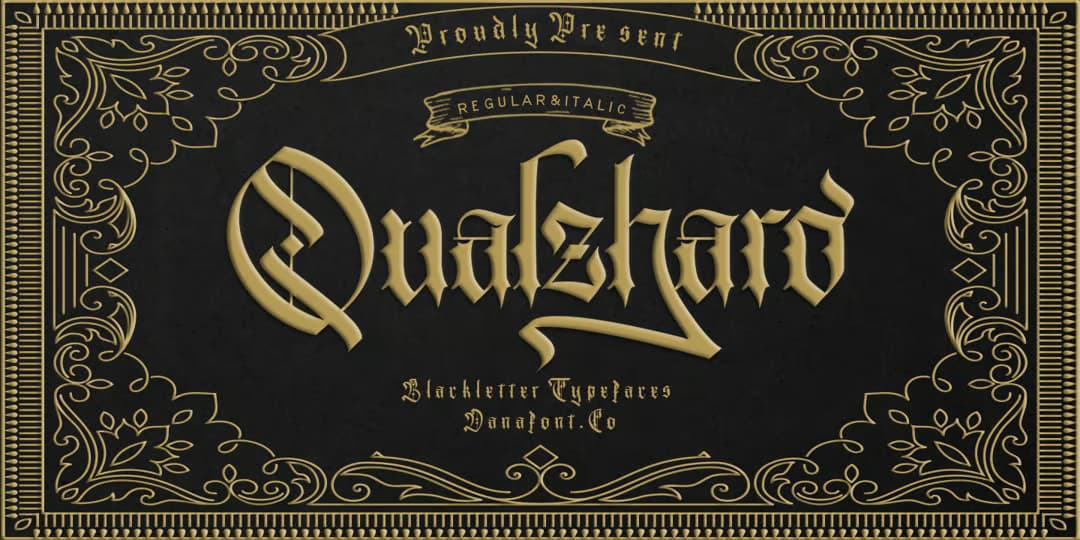
Qualzharo
非常に装飾的なブラックレター。大文字はヘアラインやダイヤなどの装飾が入っていて、小文字もストロークの端だけでなく途中にもトゲトゲした飾りが入っており、全体的にかなりデコラティブ。小文字にはスワッシュオルタネートがあるが、これも文字本体と同じ太さでかつ左方向に走るストロークが多く、アラビア文字の雰囲気があってオリエンタリズムにあふれている。作者は名前からして中東の方だろう。右に傾いたイタリックスタイルがあるのもおもしろい。名前はなんと読むのだろう…クァルザーロ?